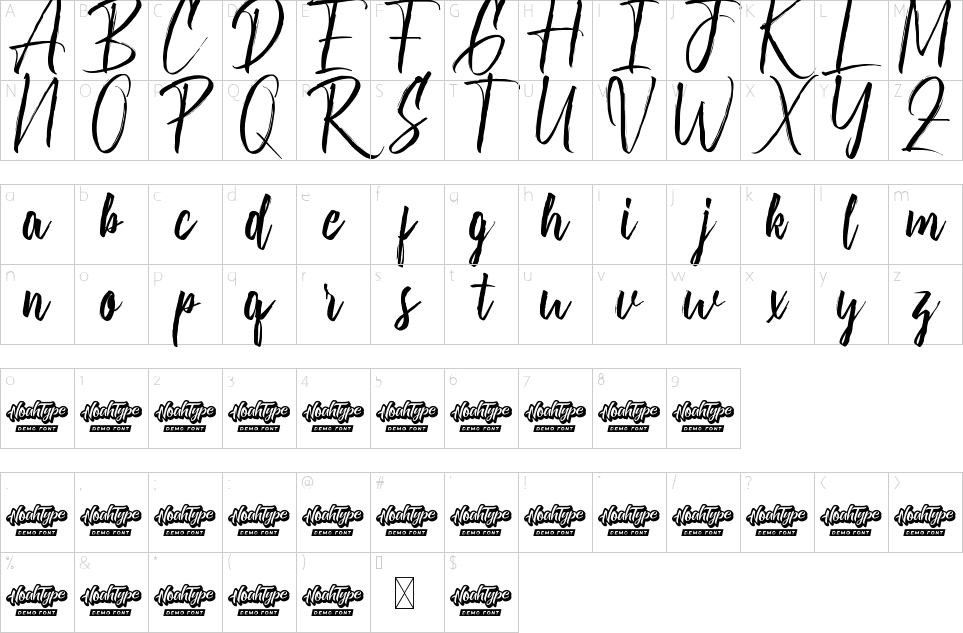
A Sanpedro é uma fonte de design minimalista e sofisticada, perfeita para personalizar textos de forma elegante e única. Esta fonte foi criada pelo designer NoahType e já foi baixada 1.224 vezes, mostrando sua popularidade entre designers e criadores de conteúdo. Com uma arquitetura de linhas levemente curvada, a Sanpedro adiciona um toque de elegância a qualquer projeto digital. Seja para criar um site elegante ou um design gráfico sofisticado, a Sanpedro é uma escolha perfeita para quem busca uma fonte minimalista e agradável ao olhar. Descubra por si mesmo como essa fonte pode transformar seu trabalho em um verdadeiro lançamento.